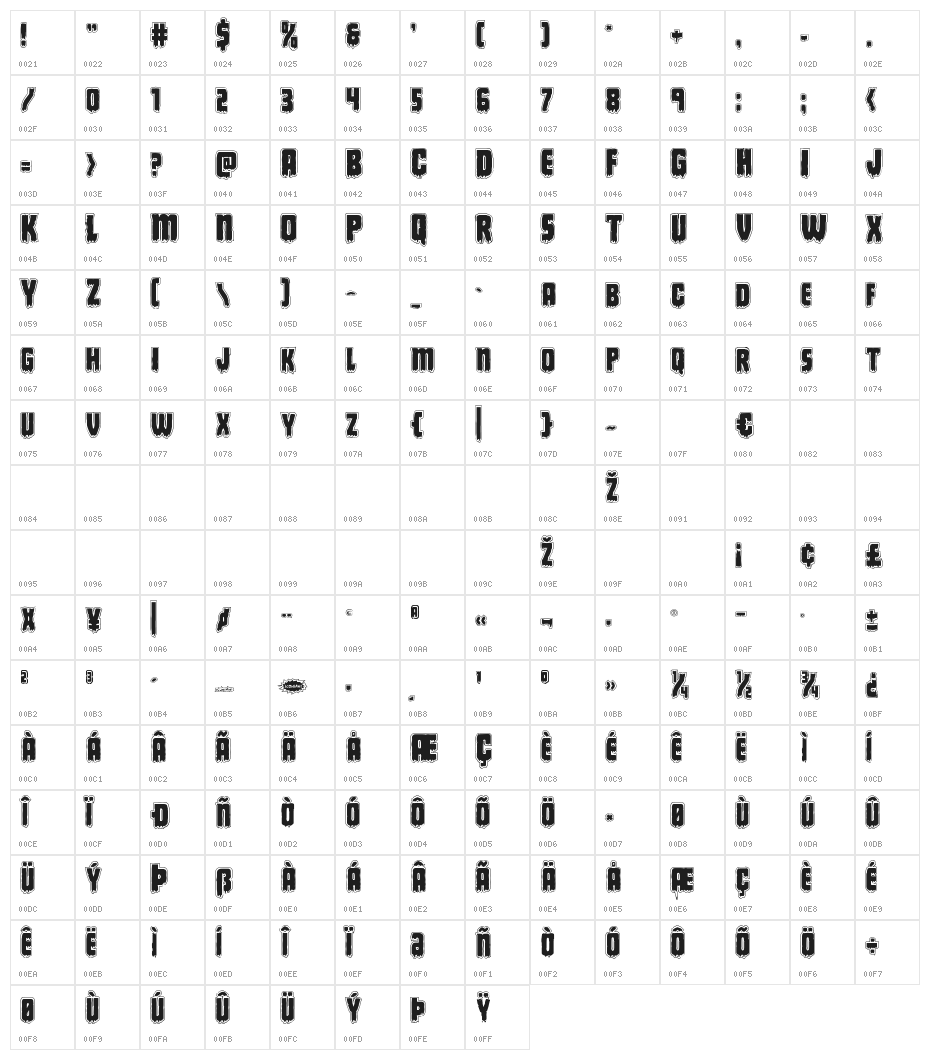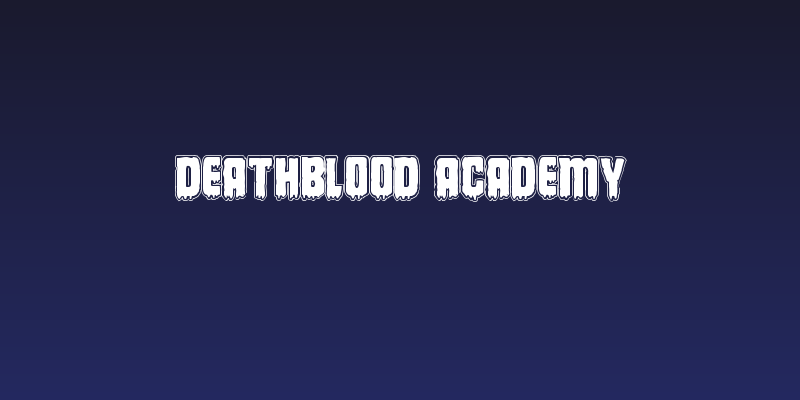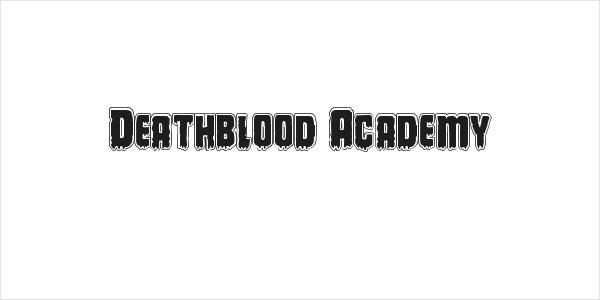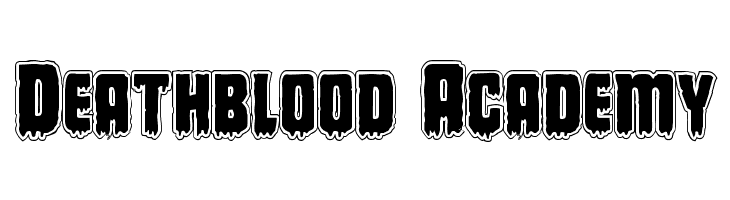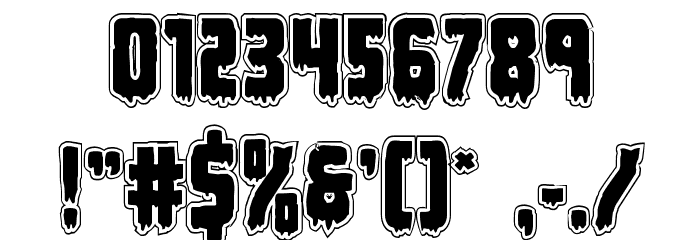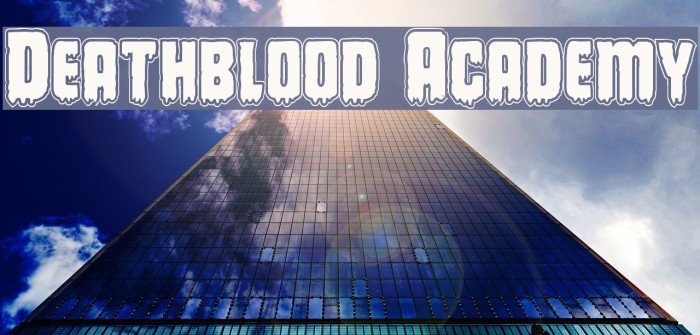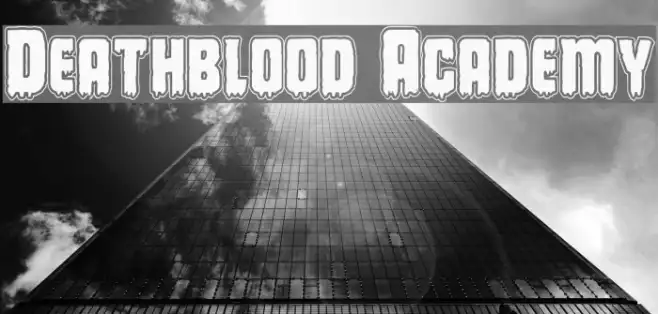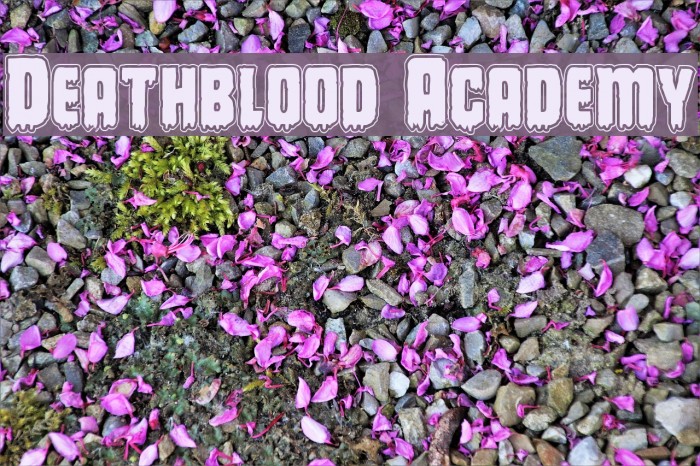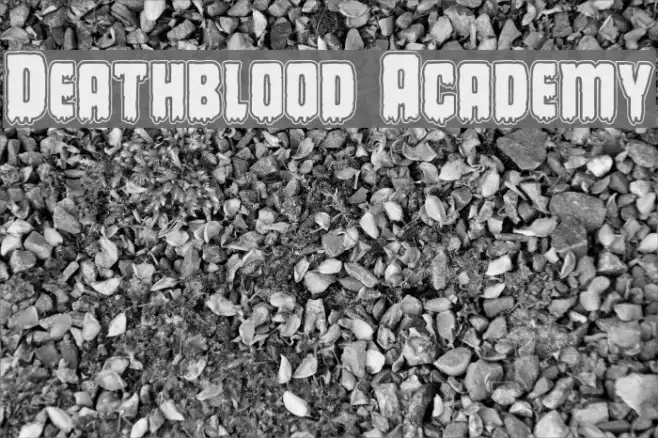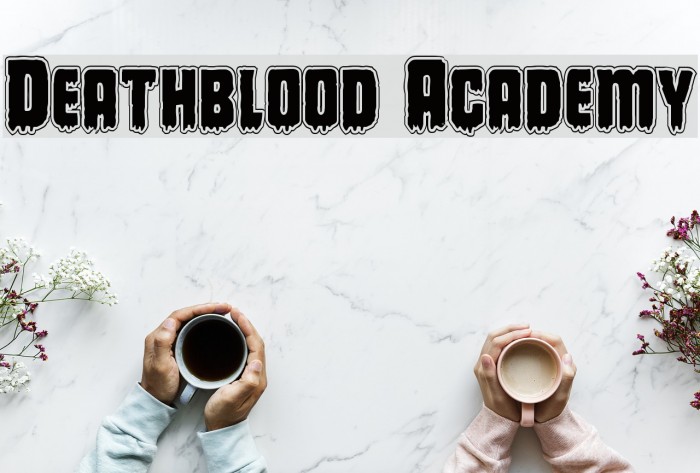
Deathblood Academy Font
| Projets proposés | Ideal for Halloween-themed designs, horror movie posters, spooky event invitations, and any project requiring a chilling, dramatic typeface. |